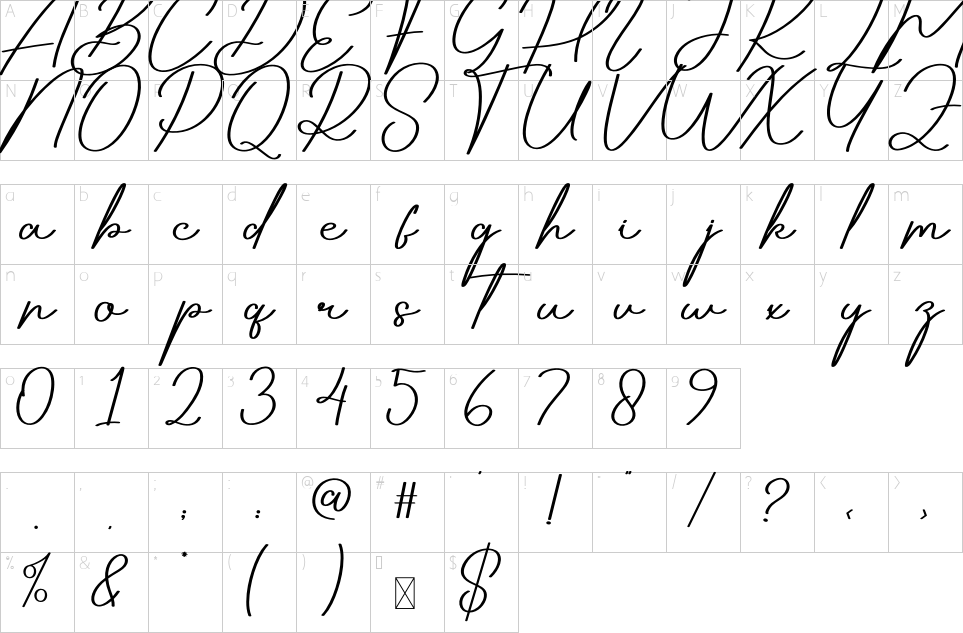
A fonte Audrey Signature é um toque elegante e sofisticado para seus projetos digitais, perfeita para anúncios, logotipos e designs de newsletter. Desenhada por scratchones, essa fonte é uma escolha ideal para quem busca uma aparência elegante e elegante em seu material gráfico. Ela foi descarregada mais de 842 vezes e é uma ótima maneira de trazer um toque de sofisticação a qualquer projeto. Para quem está procurando uma fonte com um acabamento cuidadoso, Audrey Signature é uma boa opção de fonte gráfica gratuita. Suavemente delicada, mas de uma qualidade respeitável, ela pode se adaptar a uma variedade de estilos de design. Não importa o seu objetivo, ela é uma fonte que merece um lugar no seu arsenal de ferramentas digitais.